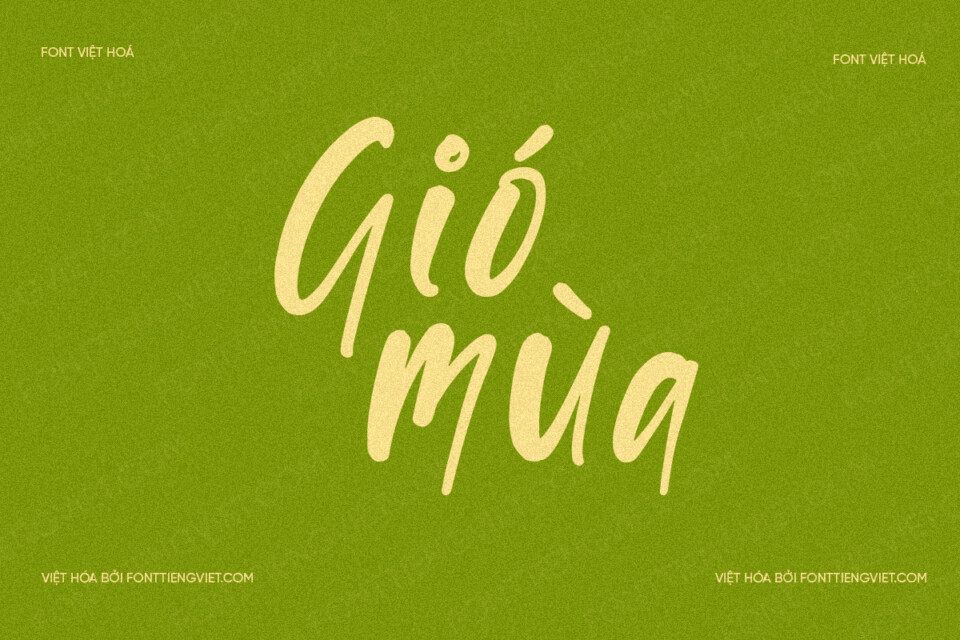
Font Việt hóa 1FTV VIP Scartoon
Khám Phá Bộ Font Việt hóa 1FTV VIP Scartoon Dành Cho Thiết Kế Hoạt Hình
Giới thiệu về sức hút của Font Việt hóa 1FTV VIP Scartoon
Trong thế giới sáng tạo đầy màu sắc của học đường, việc lựa chọn một Font Miễn Phí phù hợp đóng vai trò vô cùng quan trọng để làm nổi bật thông điệp. Bộ Font Việt hóa 1FTV VIP Scartoon nổi lên như một hiện tượng nhờ phong cách vui nhộn, đậm chất hoạt hình và tràn đầy năng lượng tích cực. Với những nét chữ tròn trịa, tinh nghịch, bộ phông này giúp các bài thuyết trình hay báo tường của học sinh trở nên gần gũi và lôi cuốn hơn bao giờ hết. Đặc biệt, phiên bản này đã được tối ưu hóa đầy đủ dấu tiếng Việt, giúp người dùng hoàn toàn yên tâm về tính thẩm mỹ mà không lo lỗi font khi soạn thảo văn bản.
Những ưu điểm vượt trội của Font Việt hóa 1FTV VIP Scartoon
Phong cách thiết kế độc đáo
Được thiết kế dựa trên cảm hứng từ các bộ phim hoạt hình nổi tiếng, Font Việt hóa 1FTV VIP Scartoon mang đến sự linh hoạt tuyệt vời cho các dự án đồ họa. Các đường nét không quá cứng nhắc mà có độ biến tấu nhẹ nhàng, tạo cảm giác thân thiện cho người xem. Đây là lựa chọn lý tưởng để làm tiêu đề cho các video ngắn, trang trí bìa vở hoặc thiết kế thiệp mời các sự kiện ngoại khóa tại trường học. Khả năng hiển thị rõ nét trên cả màn hình điện tử và bản in giúp bộ chữ này chiếm trọn cảm tình của cộng đồng thiết kế Việt Nam.
Kết luận về bộ font chữ hoạt hình ấn tượng
Việc sử dụng đúng phông chữ sẽ giúp bạn truyền tải cảm xúc một cách trọn vẹn nhất đến bạn bè và thầy cô. Đừng ngần ngại tải ngay bộ Font Miễn Phí, Font Việt Hóa, Font Việt hóa 1FTV VIP Scartoon để biến những ý tưởng đơn giản thành tác phẩm ấn tượng. Hãy để sự sáng tạo của bạn bay xa cùng bộ chữ độc đáo này ngay hôm nay.